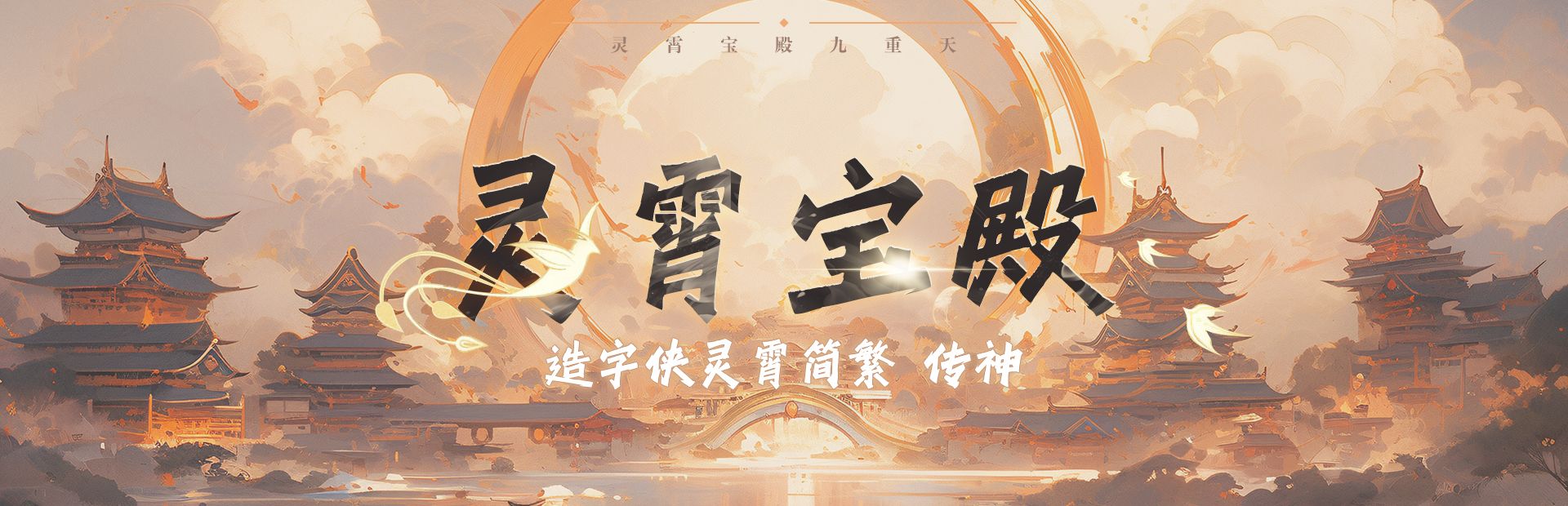
神佛之战,战至巅峰,神魔游戏类字体推荐——造字侠灵霄简繁 传神
《西游记》作为中国四大名著之一,以生动奇幻的文字讲述了西行取经的故事,同时也是一部完善整合中国神话体系的文学史诗,各有缺点的师徒四人齐心协力渡过九九八十一难,最终取得佛经修成正果。天庭各色神仙的开篇,充满神话色彩,开辟了很多围绕着天庭创新了了很多百般神通、法力高强的仙侠游戏故事。
励字造梦共创字库推出一款古风奇幻的游戏字体——造字侠灵霄简繁 传神,是一款硬笔手写字,名字来源于《西游记》玉皇大帝的居所灵霄宝殿。字体笔画硬挺利落,字形古风劲萧,饱满均匀,结构布局沉稳,笔力劲健,适用于仙侠、网游等海报标题用字。